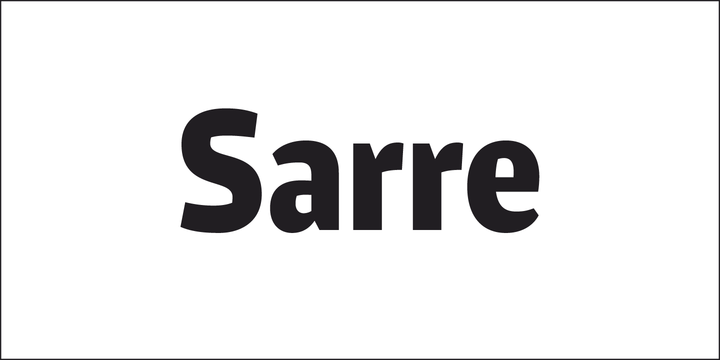
Descubra uma nova aventura no mundo das fuentes com a Sarre Font Family, criada pelo designer Hamilton para as categorias de fuentes sans serif. Essa família de fontes oferece um sentido único e moderno do design, trazendo você muitas opções em seu catálogo de fontes. A Sarre é uma fonte cuidadosamente projetada com características equilibradas, versáteis e alegres, ideal tanto para uso como texto quanto para aplicar em tamanhos maiores, onde revela um estilo limpo e elegante. Com o propósito de ser apreciada e diversificada, ela foi criada para ser uma amiga fiel e uma fonte divertida para você usar. Esta família de fuentes traz a liberdade de expressão de uma sans serif moderna com um toque fresco e único. Ideal para os designers que buscam algo novo e inspirador em seus projetos, seja para criar identidades digitais ou trabalhos de texto, a Sarre Font Family está aqui para oferecer flexibilidade e beleza em cada letra. Não espere mais – introduzindo o talento do designer Hamilton à sua coleção de fontes, você já pode começar a explorar seu potencial criativo!